各位好~ 最近在筹划制作一套化妆品包装,所以写了这篇文章。
目前打算制作的是一款以红月亮为元素的化妆品套装——这个设计元素的灵感来自蓝月亮,但我毕竟不是真的在为蓝月亮做包装,所以为了避免可能存在的纠纷,我虚构了一个IP。
~~(什么?你说蓝月亮不是搞化妆品的?那不重要。面部清洁怎么不算一种清洁呢,说不定以后他们就做了ᕕ( ᐛ )ᕗ)~~
说起来对于不同产品的包装设计,在风格上的区别还挺大的。
食品包装大概是因为产品比较多,为了能够促进消费,外观设计一般都比较吸引眼球,争取摆在货架上能让消费者一眼就看到。尤其是一些主打儿童食品的产品。
而对于化妆品包装,消费用户画像大多为青年及中年群体,这个类别不说全是高端吧,但起码是中端以上。这时候如果再用吸引眼球的花哨设计,反而会让人感觉廉价。
所以,简约就好昂~
目前套装大概暂定为:精华、面霜、洗面奶,建模过程感觉没啥好讲的,和设计也没什么关系,这里就跳过了。
接下来,我会挨个介绍我的设计思路。
红月精华液
刀模
以前的包装设计好像大多是先射箭后画靶……也就是先设计好包装,再补上一个产品。这会倒是不一样了,我先建的模。
具体外盒尺寸是根据模型来的,使用快捷键Shift+A新建一个立方体,然后使用缩放以及拉伸调整尺寸,然后打开透视模式来查看立方体是否能够包裹产品即可。如下图,可看出纸盒的比例可为1.5:1.5:3.8,只需要符合这个比例就行,到时候导入材质和UV贴图的时候是可以进行缩放调整的。
然后我还查了一下同类产品的大概尺寸,看到不少有几款 100ml精华液 的尺寸差不多是 50mmx50mmx180mm,那按照我这的比例,外盒尺寸可以设计成 50mmx50mmx130mm 左右。精华的结构设计有高有矮,高度上短一点倒也不算什么大事。
然后接下来就是最省事的部分了,去包小盒整个刀版结构图即可。具体过程我就不写了,都是傻瓜式操作。导入到AI后如下:
接下来就是进行设计了~ 之前学的印刷知识此刻倒是总算有了用武之地。
说起来以前在学校交的设计文件全是用的RGB,漏洞百出啊,交的作业没几个能用的,老师全是都是能交差就完事,哎~~(RBG是光学色彩,印刷文件一般得使用四分色模式(CMYK)。学校课程倒是有教导,但是实际用的时候完全没人提,坑人了不是)~~。
版式
在设计之前,需要先整理一下一些相关的法律法规要求。毕竟这次可不是学校的作业了,要保证设计出来的东西具有实用价值。目前考虑到的法规主要是《化妆品标签管理办法》,其次是《广告法》和《化妆品监督管理条例》。
目前简单总结一下,主要是需要避免一些医疗用语和功效夸大、安全性保证及绝对性用语,然后标注信息要包括:产品中文名称、特殊化妆品注册证书编号、注册人/备案人名称地址(境外企业需标注境内责任人)、生产企业名称地址(国产化妆品需生产许可证编号)、产品执行标准编号、全成分、净含量、使用期限、使用方法、安全警示用语、其他规定内容。
| 条款 | 化妆品标签设计法规 |
|---|---|
| 第六条 | - 应当以中文标签为主,其他文字或符号需在可视面用规范汉字对应解释(网址、专业名词等情况可例外) - 其他文字字号应小于或等于规范汉字。 |
| 第七条 | - 化妆品中文标签应当至少包括:产品中文名称、特殊化妆品注册证书编号、注册人/备案人名称地址(境外企业需标注境内责任人)、生产企业名称地址(国产化妆品需生产许可证编号)、产品执行标准编号、全成分、净含量、使用期限、使用方法、安全警示用语、其他规定内容; - 具有包装盒的产品,还应当在直接接触内容物的包装容器上标注中文名称和使用期限。 |
| 第八条 | - 产品中文名称由商标名、通用名、属性名组成,约定俗成、习惯使用的化妆品名称可以省略通用名或者属性名。 - 商标名不得宣称医疗效果或虚假功效(含原料相关名称时需说明使用目的,或标注不含材料仅作商标使用);通用名需准确客观(与配方和功效相符);属性名需表明产品真实物理性状或者形态,并应主动避免歧义。 |
| 第九条 | - 化妆品中文名称应在可视面显著位置进行标注,且不得使用其他文字或符号进行命名(防晒指数等术语可例外)。产品中文名称中的注册商标使用其他文字或符号的,应当对其含义进行解释说明。 |
| 第十条 | - 注册人/备案人、境内责任人、生产企业名称地址等信息应以引导语引出;化妆品注册人与生产企业相同时,可简化标注(如“注册人/生产企业”);生产企业信息应标注完成最后工序的企业;国产化妆品需标注生产许可证编号。 |
| 第十一条 | - 化妆品标签应在包装可视面标注产品执行标准编号,以引导语引出。 |
| 第十二条 | - 化妆品标签应当在包装可视面标注全部成分的原料标准中文名称,以“成分”引导语引出,并按按含量降序列出;微量成分(≤0.1%)以“其他微量成分”引导另标(可不按序)。 |
| 第十三条 | - 化妆品的净含量应使用国家法定计量单位,在展示面标注。 - 且根据《定量包装商品计量监督管理办法》,字高应符合: ≤50g为≥2mm,50g~200g为≥3mm,200g~1000g为≥4mm |
| 第十四条 | - 使用期限标注方式:生产日期和保质期(格式为YYYY-MM-DD)或生产批号和限期使用日期; - 小包装可标开封后期限;多独立包装标注最早到期日或分别标注。 |
| 第十五条 | - 使用方法应在可视面或说明书中标注。 |
| 第十六条 | - 安全警示用语以“注意”或“警告”引导语引出,在可视面标注(适用于限用组分、儿童产品等情形)。 |
| 第十七条 | - 面积小于10cm²且净含量≤15g或15mL的小规格包装,仅需标名称、注册证书编号、注册人/备案人名称、净含量、使用期限,其他信息可标注于产品说明书。 - 具有包装盒的小规格包装产品,还应当同时在直接接触内容物的包装容器上标注产品中文名称和使用期限。 |
| 第十八条 | - 创新用语需在相邻位置解释说明其含义。 |
| 第十九条 | - 禁止标注内容:医疗术语及医疗效果暗示、误导性暗示、伪科学概念、贬低竞品、虚构数据、虚假或夸大功效、无证标识、利用国家事业单位及个人作证明、功效及安全性的保证、违反社会公序良俗、绝对化用语等违规情况 |
然后接下来就简单的调整一下版式吧,删掉包小盒自带出血线及颜色填充,然后设置画板自动适应图稿边界,在文档设置里设置出血线为3mm就做好了。剩下的色彩条、套准、角线等标记在导出的时候会自动生成,所以只需要在尺寸上设计好即可。
设计
嗯,接下来就是正式的平面设计了,目前元素已经确定了是红月亮,在设计产品之前,我需要先设计一个Logo。
之前我倒是有设计过一个红月Logo,但那个是游戏图标,中文字体也不符合标签法规。对化妆品来说,设计还是越简洁越好。毕竟连京东、淘宝之类的App现在也是设计成纯平面简约风格了,在审美这块还是向大厂看齐吧。
然后再说回 logo,目前设计思路主要有两个方向:一个是以红月的英文或者中文字符来进行设计;另一个则是以月亮图形为元素为设计。这次就以字符为主要设计方向吧,如下图:
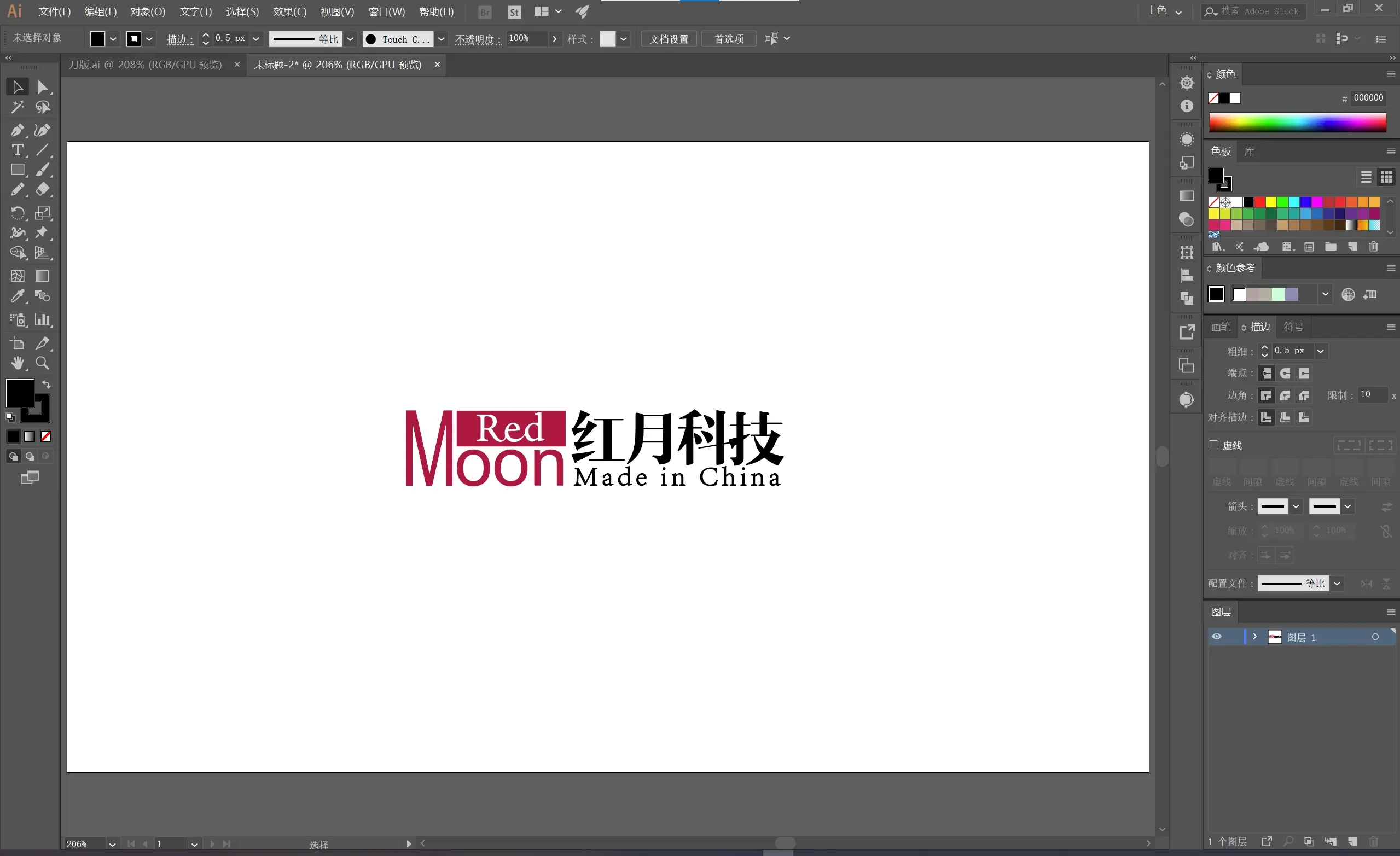
这是大概的一个样式。目前来看的话,红框里还是有些违和,大概是因为字体与其他英文不同,外加两侧空白有点多。
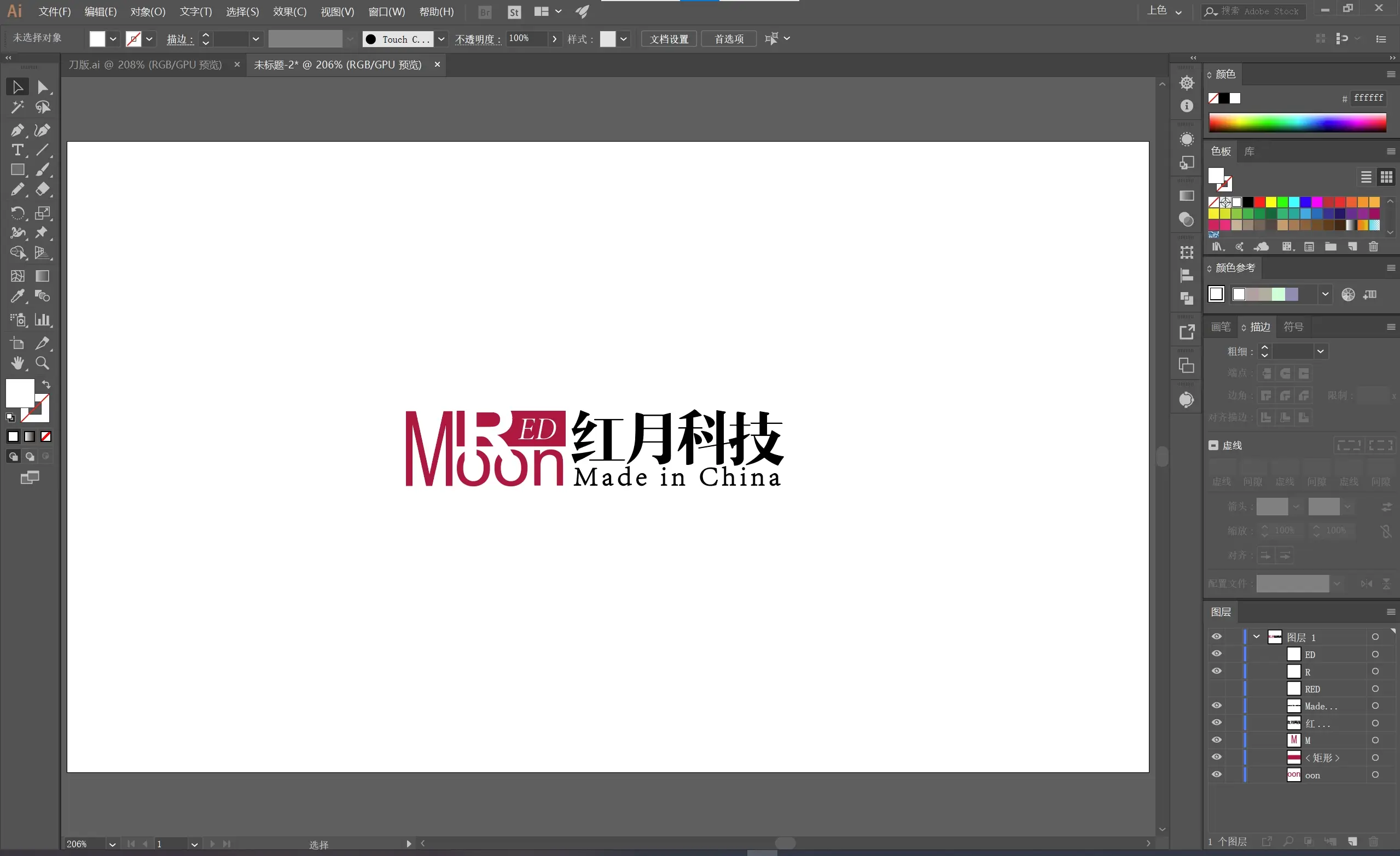
调整后好了一些,但还是怪怪的,应该还是字体样式用了太多的问题,而且视觉比重不对的问题还是没有解决,空白依旧有点多。还得再调整一下。
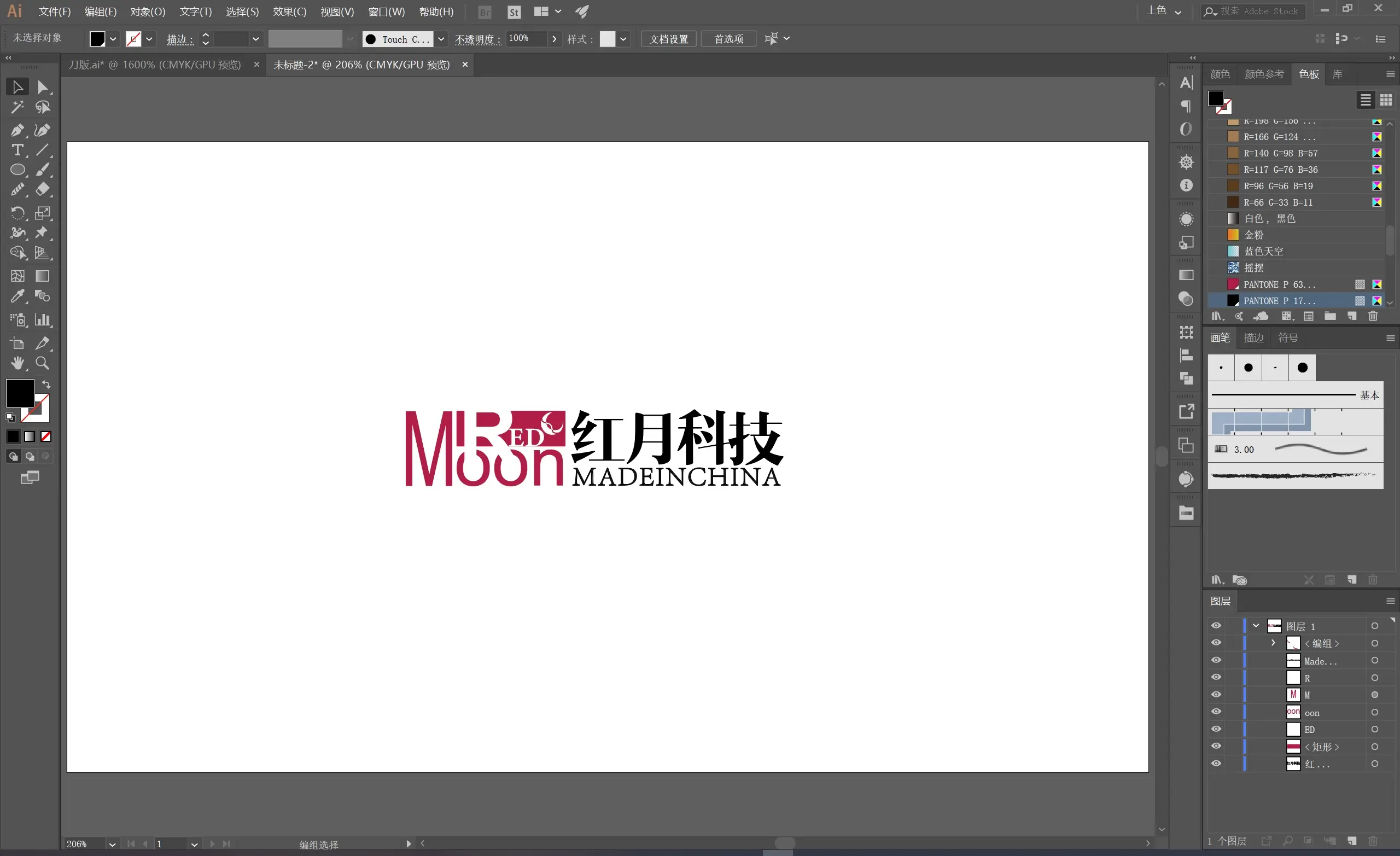
现在看着倒是舒服一些了,不过目前虽然是优化了视觉比重,东西却还是有点太多,显得有些繁杂。等会做平面设计的时候放上去看看会不会太花哨吧,如果看着感觉不自然就再调整。
Logo的大概样式设计好以后,还需要转成CMYK模式来调整印刷色。
这里使用的方法是编辑→编辑颜色→重新着色图稿→PANTONE+ CMYK Coated,色卡是潘通 CMYK 的四色模拟,AI会自动选择颜色最相近的潘通色号。这样就可以尽可能减少印刷误差了。
~~(PS:记得把黑色改成单黑。)~~
接下来就正式开始盒型设计了,目前根据我们的元素,盒子底色预计是采用红白双色,其中以白色为主。
毕竟走简约风格的话,确实还是白色最适合。